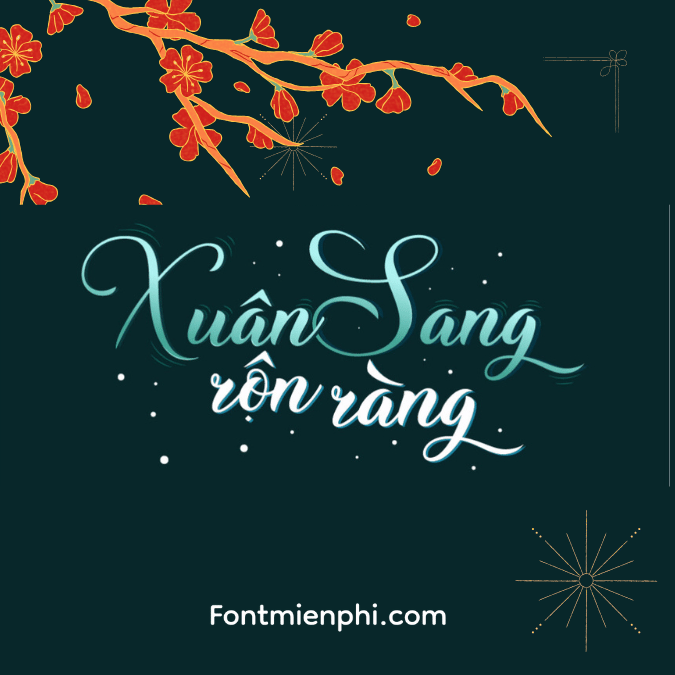
Font Việt Hóa 1FTV VIP Christmas Wish Calligraphy – Kiểu Chữ Nghệ Thuật Đón Giáng Sinh 2024
Giới Thiệu Font Christmas Wish Calligraphy
Font 1FTV VIP Christmas Wish Calligraphy là bộ font chữ nghệ thuật cao cấp, được thiết kế riêng cho mùa Giáng Sinh và Tết Dương lịch 2024. Với nét chữ uốn lượn mềm mại cùng họa tiết tuyết rơi, cành thông cách điệu, font chữ này trở thành lựa chọn hoàn hảo cho các thiết kế mang đậm không khí lễ hội.
✨ Đặc Điểm Nổi Bật
✅ Phong cách Calligraphy sang trọng: Nét thanh đậm tự nhiên, mềm mại như viết tay
✅ Tích hợp 50+ glyph đặc biệt: Họa tiết Giáng Sinh (cây thông, ngôi sao, quả châu, gấu Bắc Cực)
✅ Tối ưu cho tiếng Việt: Hỗ trợ đầy đủ dấu, đọc mượt ở mọi kích thước
✅ Hiệu ứng “Winter Magic”: Tự động phủ ánh bạc như tuyết trên nét chữ
Ứng Dụng Font Christmas Wish Calligraphy